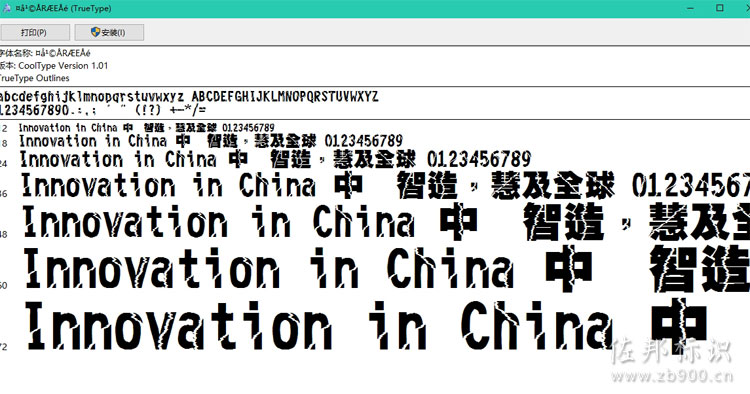
文鼎霹雳体繁体字体是一款个性化十足的字体,有别于一般的文鼎字体,该字型非常漂亮,承霹雳状,具有刚正不阿的感觉和野性十足的感觉,不拘一格。佐邦科技官网提供文鼎霹雳体繁体字体下载,有兴趣的设计师赶紧来佐邦科技官网免费下载吧!
文鼎霹雳体繁体字体介绍
文鼎霹雳繁体字是一款设计风格十分独特的汉语字体,方正、齐整,字体又有一点分岔的小心机设计方案,十分时尚潮流。